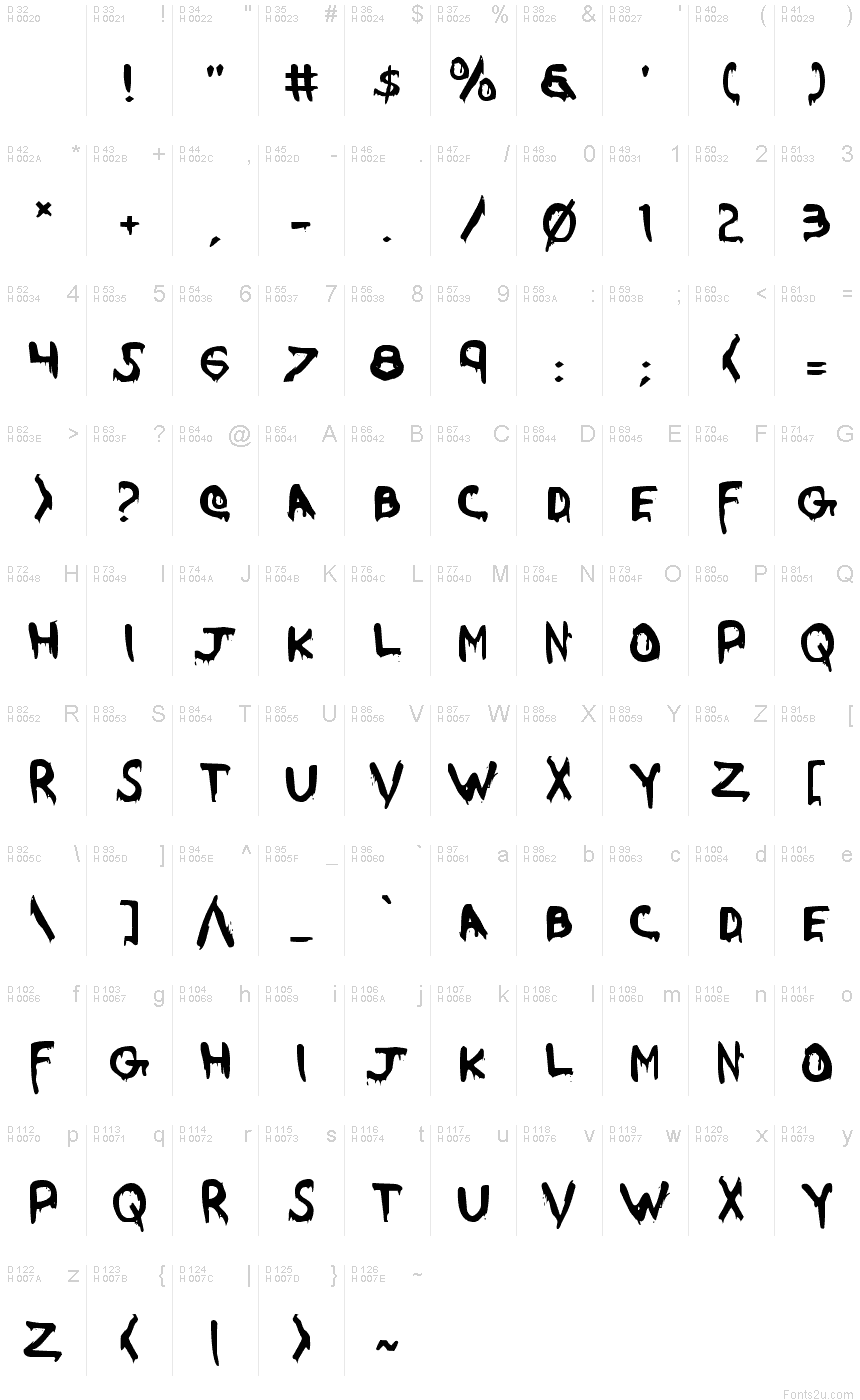
Were-Beast od Iconian Fonts (2008) to darmowy, zniekształcony krój horrorowy typu display z poszarpanymi, nierównymi literami, które wyglądają, jakby zostały wydrapane pazurami. Wypaczone krawędzie, ostre cięcia i okazjonalne zacieki nadają znakom dzikiego, ręcznie wykonanego złowrogiego charakteru, bez zbędnych ozdobników.
Postrzępiona sylwetka liternictwa tworzy klimat niczym z filmu o potworach na plakatach grozy czy ekranach tytułowych gier. Ten darmowy font sprawdzi się również na szyldach nawiedzonych domów, zaproszeniach na Halloween, okładkach albumów czy w mrocznych grafikach, gdzie jego chwiejny rytm świetnie współgra z potworami, dymem czy posępnymi obrazami.